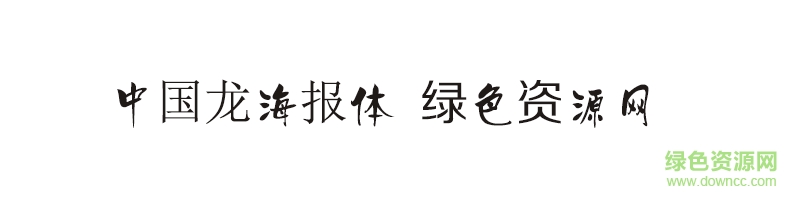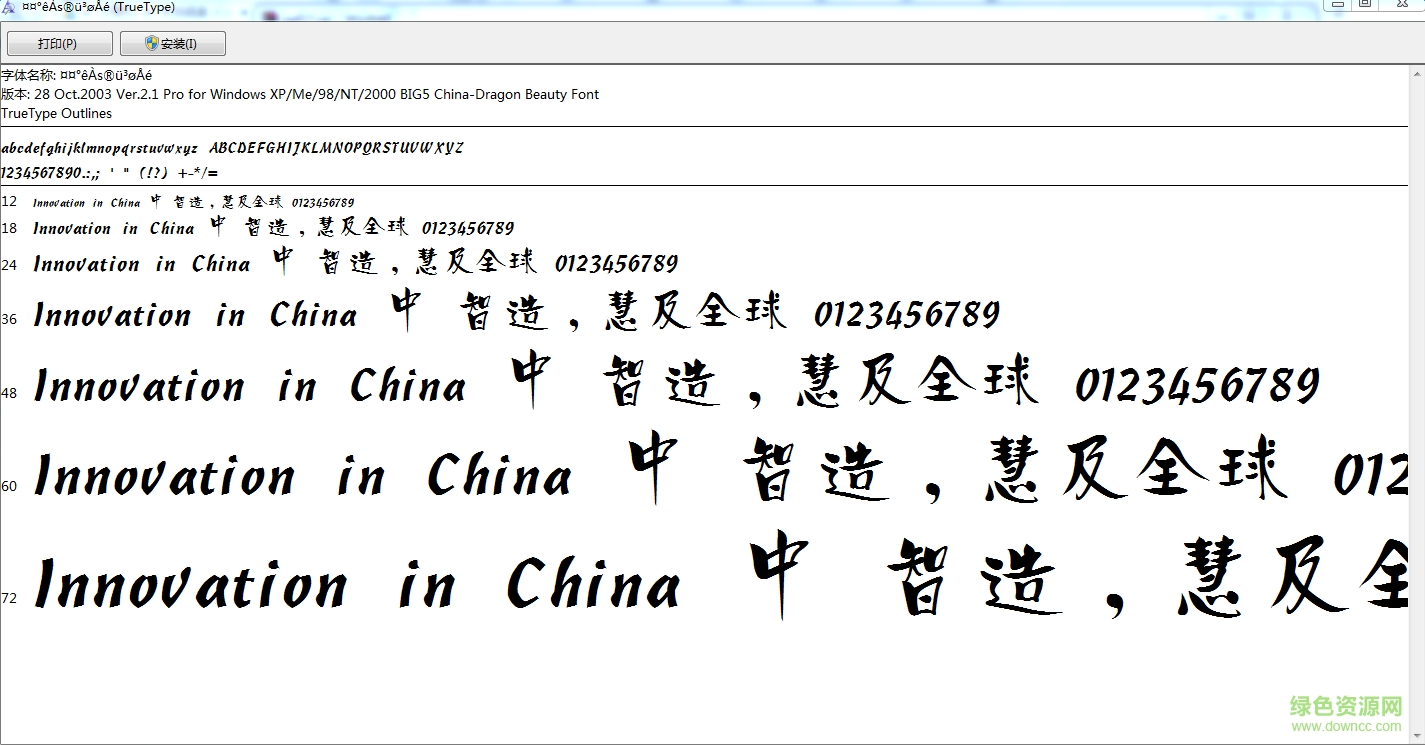
中國(guó)龍海報(bào)體字體是一款中國(guó)風(fēng)海報(bào)類(lèi)字體軟件,字體工整好看,給人一種整體舒服的感覺(jué),適合各種海報(bào)雜志,非常養(yǎng)眼,喜歡的朋友歡迎來(lái)綠色資源網(wǎng)下載體驗(yàn)!
在藝術(shù)設(shè)計(jì)和各種商業(yè)海報(bào)的制作中,字體的風(fēng)格選擇是十分重要的,不同的風(fēng)格字體都會(huì)造就不同的視覺(jué)效果。而中國(guó)龍海報(bào)體是一套充滿(mǎn)中國(guó)風(fēng)的中文字庫(kù),綠色資源網(wǎng)給大家提供好看的中國(guó)龍海報(bào)體字體!